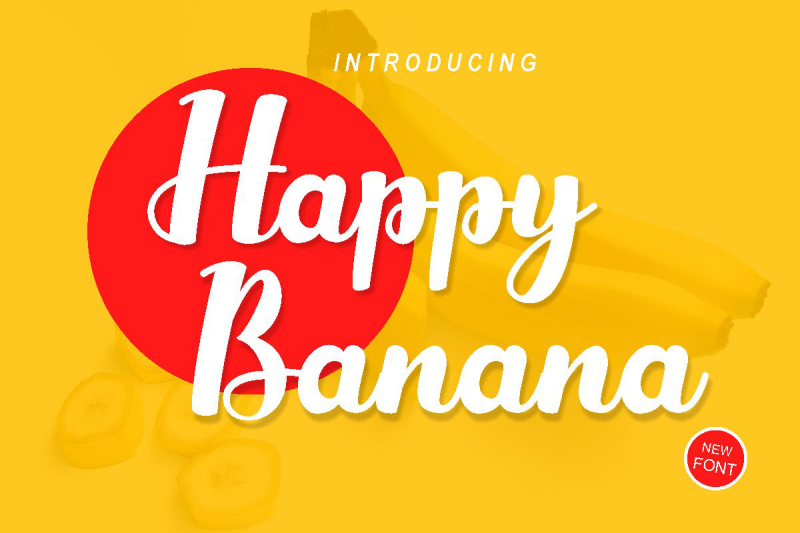
Happy Banana Font – Fonte Grátis
Happy Banana Font
A fonte ‘Happy Banana Font’ é uma mão-dura que captura a elegância e a tendência atual com um toque de simplicidade. Ela se destaca perfeitamente em qualquer design, especialmente nas ocasiões especiais como convites de casamento ou cartas de agradecimento, mas também atende à necessidade de personalização nos selos de cartas de cumprimentos e frases que carregam um toque único. Seja para uma decoração elegante no seu apartamento ou para dar um toque especial em qualquer design digital, ‘Happy Banana Font’ é perfeita para quem busca customização sem abrir mão do encanto contemporâneo da fonte. Através de sua escrita agradável e descontraída, a font oferece uma variação única que se destaca enquanto mantém um toque de simplicidade elegante.